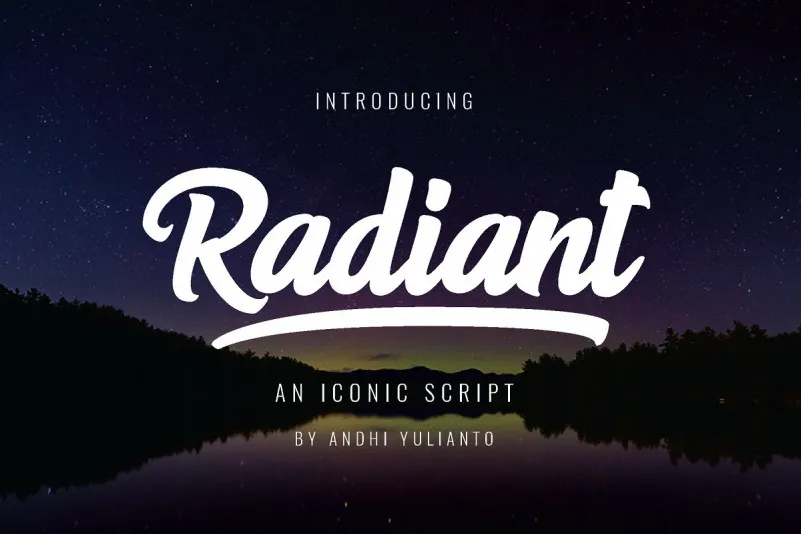
Radiant Bold Script Font
A M.0Type nos apresenta Radiant Bold Script Font, uma nova adição para a família dos fonts script bold. Este é um tipo de letra poderoso e dinâmico, ideal para criar logos e logotipos. Radiant Bold Script oferece uma solução versátil para projetos como roupas ou qualquer aplicação onde você queira transmitir confiança através de sua marca. Perfeito para designers de roupas, o estilo bold da font é ótimo para destacar em estampas e peças. Também é perfeito para criações visuais como a criação de citas e mensagens. Seja um design gráfico mais casual ou uma mensagem forte em um logotipo sofisticado, Radiant Bold Script oferece o que há de melhor no tipo de letra script. Com seus traços simples mas poderosos, esta font é perfeitamente adequada para projetos de marca, pois não apenas ajuda a destacar sua identidade visual, mas também torna seu logo único e memorável. Radiant Bold Script foi feito à mão com um pincel, depois digitalizado cuidadosamente usando software vetor. O resultado final é uma fonte equilibrada e proporcionalmente correta. Não importa o tipo de projeto em que esteja envolvido, a M.0Type pode proporcionar um toque único e poderoso para seu trabalho visual.